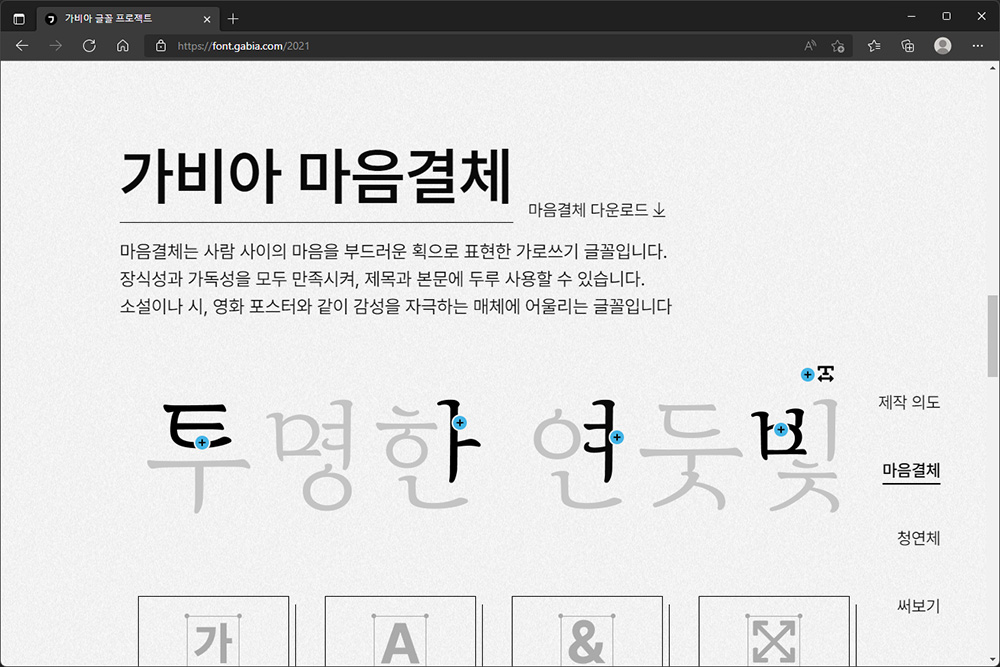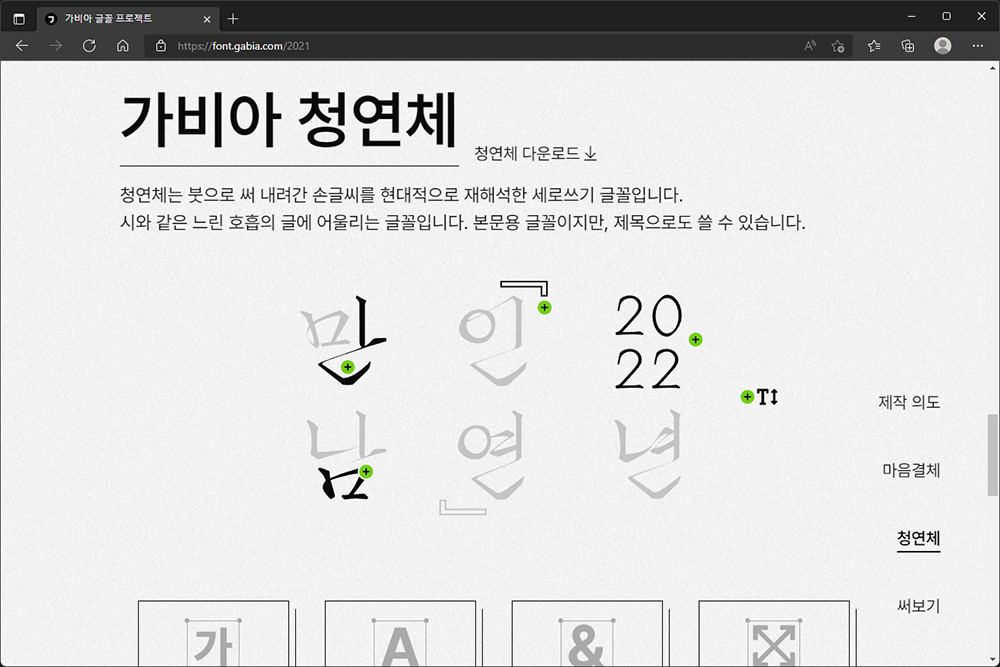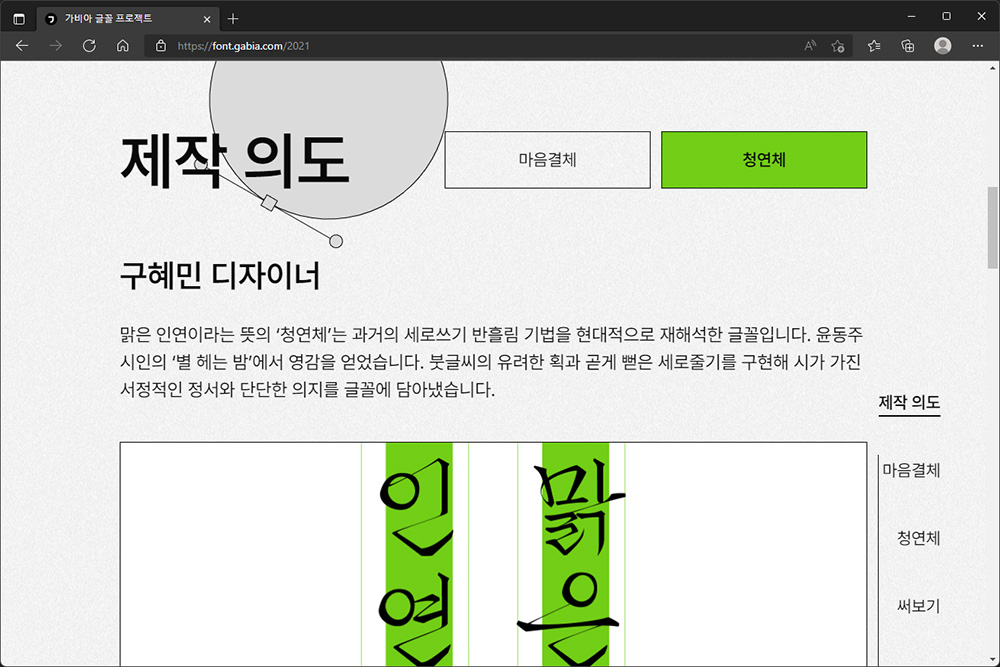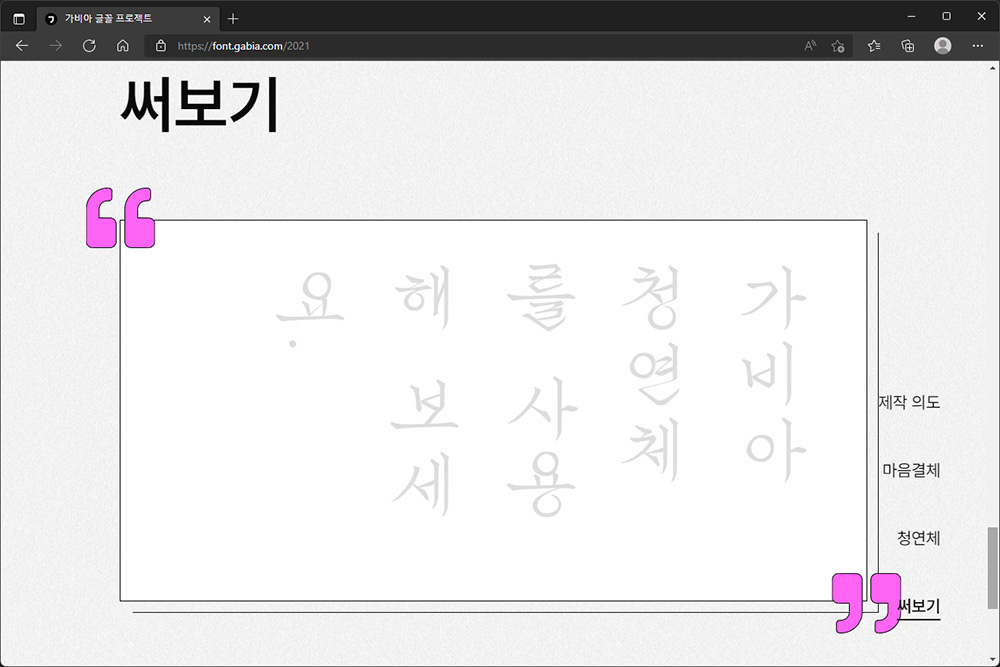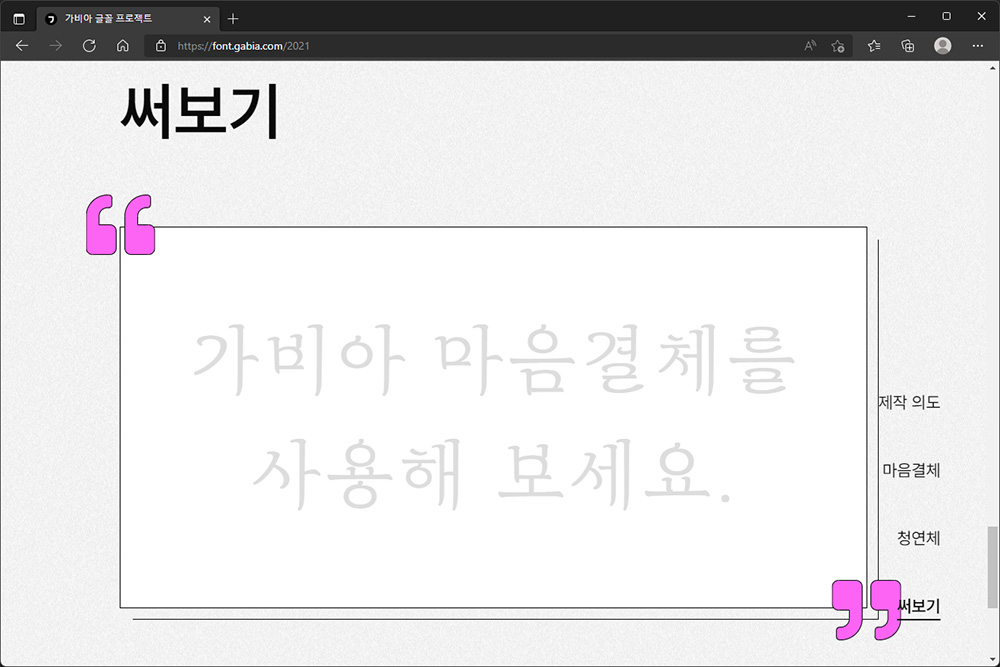
상업적 무료 폰트! 가비아 글꼴 프로젝트 마음결체, 청연체!
사진이나 동영상 콘텐츠를 제작하다 보면 간단하게 새로운 분위기를 연출할 수 있는 폰트에 관한 관심이 높아지고 자연스럽게 다양한 폰트들을 수집하게 됩니다. 특히 폰트 저작권은 굉장히 중요하기 때문에 항상 신경을 쓰고 있어야 합니다. 그래서 이번 포스팅에서는 궁서체를 대체할 수 있는 상업적 무료 폰트 가비아 글꼴 프로젝트 마음결체, 청연체에 대해서 자세하게 확인해 보도록 하겠습니다.
가비아 글꼴 프로젝트 마음결체의 경우에는 박주원 디자이너에 의해서 제작이 되었고 사람 사이에 오가는 마음을 시각적으로 표현을 했다고 합니다. 저는 특히 글꼴의 끝 부분의 표현이 인상적이었습니다.
가비아 글꼴 프로젝트 마음결체의 경우에는 가독성이 상당히 좋은 편이어서 소설이나 시 그리고 영화 포스터와 같이 감성을 자극하는 매체에 적합한 폰트입니다. 표시를 만들 때 활용하면 좋을 것 같습니다.
가비아 글꼴 프로젝트 청연체는 구혜민 디자이너에 의해서 제작이 되었고 과거의 세로쓰기 반흘림 기법을 현대적으로 재해석했다고 합니다. 윤동주 시인의 ‘별 헤는 밤’에서 영감을 얻었다고 하는데요. 저는 전체적으로 폰트에 힘이 있는 편이라고 판단되었습니다.
가비아 글꼴 프로젝트 청연체는 붓으로 쓴 손글씨를 현대적으로 해석을 했다고 하는데요. 궁서체 대용으로 활용할 수 있다고 생각이 되었었습니다. 사진이나 동영상의 요소요소에 포인트를 주고 싶을 때 활용하면 좋을 것 같습니다.
지금까지 가비아 글꼴 프로젝트의 폰트들은 다운로드 받고 설치하는 방법까지 자세하게 확인해 보았습니다. 상당히 가독성이 좋은 편이고 특히 청연체의 경우에는 힘이 있는 스타일이어서 포인트가 필요한 순간에 활용할 수 있을 것으로 예상하니다. 저는 개인적으로 강력 추천합니다.